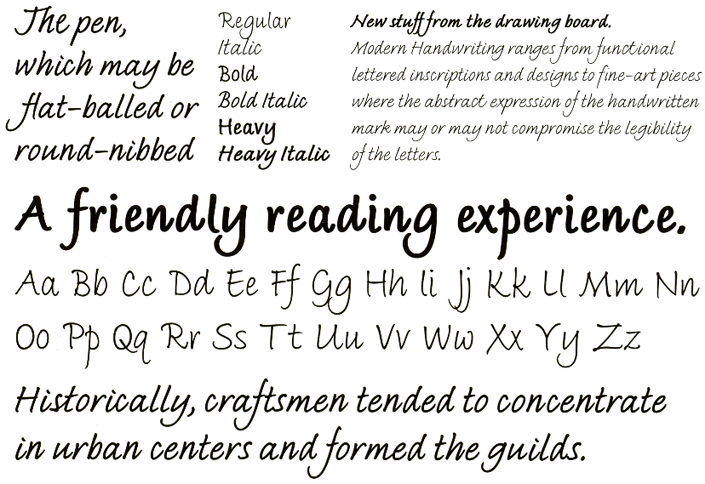
Detale, które pomagają w odbiorze kroju ITC Bradley Hand™ w mniejszych stopniach pisma, mogą dla niektórych osób być trochę rozpraszające dla tekstów składanych w większych rozmiarach. Bradley Type™ jest trochę miękki, bardziej wyrafinowany i odrobinę skondensowany - szczególnie przydatny w sytuacjach, gdy zależy nam na oszczędności miejsca. Krój ten może być stosowany jako dodatek lub odpowiednik kroju Bradley Hand lub samodzielnie do składu małych porcji tekstu lub nagłówków.
Richard Bradley wyjaśnia: „Zaprojektowałem rodzinę fontów dla zwykłych użytkowników komputerów domowych jak też dla i profesjonalnych grafików tworzących przekazy słowne. Dla każdego, kto szuka kroju pisma ręcznego, ITC Bradley Hand™ może być używany w różnych rozmiarach dla różnych projektów.”
Dla większej wszechstronności, jest on dostępny w trzech odmianach grubościowych, od wersji Regular, poprzez wersję Bold, kończąc na wersji Heavy. Dodatkowym atutem fontów z tej rodziny jest duża liczba ligatur i znaków w wersjach alternatywnych dodających do projektu troszkę szyku...